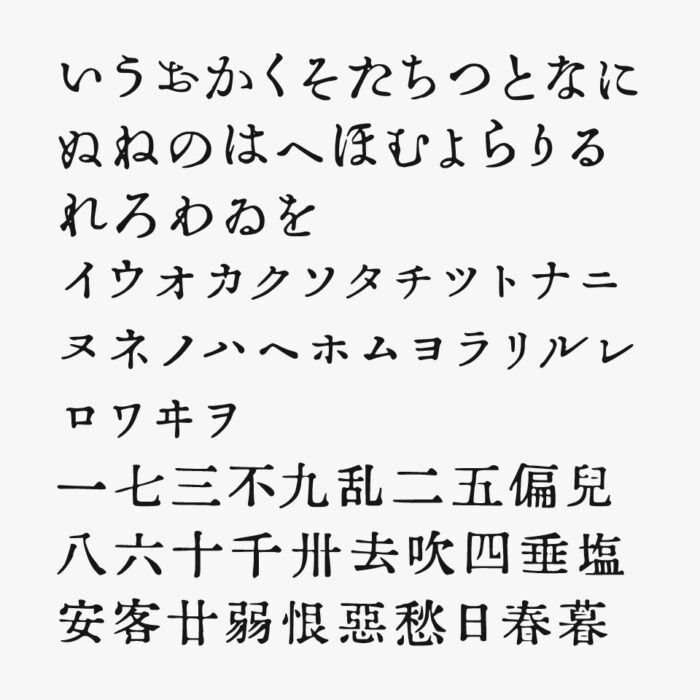
ICHIGAYA明朝体
ICHIGAYA明朝体フォントは、秀英舎活版製造所の活字をベースに制作された明朝体フォントです。
活字由来の風格を残しつつも、どこか人間味のある造形が魅力です。明朝体の端正さに加えて、印刷のにじみ感やインク溜まりが、レトロで詩的な表情を感じる明朝体フォントです。
一部の文字をピックアップしてみましたが、昔ながらの活版印刷を思わせる歪みも再現されており、重厚感やヴィンテージ感を備えた素敵なフォントです。